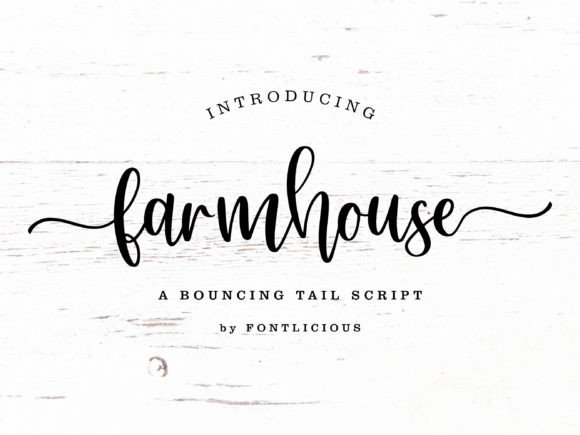
Farmhouse
์˜ฌ๋ฐ”๋ฅธ ๋””์ž์ธ ์š”์†Œ๋ฅผ ์ฐพ๋Š” ๊ฒƒ์€ ์–ด๋ ค์šธ ์ˆ˜ ์žˆ์ง€๋งŒ Farmhouse๋Š” ์ž‘์—…์„ ์ฆ‰์‹œ ํ–ฅ์ƒ์‹œํ‚ค๋Š” ๋›ฐ์–ด๋‚œ ์ปฌ๋ ‰์…˜์„ ์ œ๊ณตํ•ฉ๋‹ˆ๋‹ค.
์ •๋ฐ€ํ•˜๊ฒŒ ์ œ์ž‘๋œ Farmhouse๋Š” ๊น”๋”ํ•œ ๋ฒกํ„ฐ, ๋ถ€๋“œ๋Ÿฌ์šด ํƒ€์ดํฌ๊ทธ๋ž˜ํ”ผ ๋ฐ ์•ˆ์‹ฌํ•  ์ˆ˜ ์žˆ๋Š” ์ƒ์—…์šฉ ๋ผ์ด์„ ์Šค๋ฅผ ์ œ๊ณตํ•ฉ๋‹ˆ๋‹ค.
POD(์ฃผ๋ฌธํ˜• ์ธ์‡„) ์ œํ’ˆ, ๊ฒฐํ˜ผ์‹ ์ดˆ๋Œ€์žฅ ๋˜๋Š” ์†Œ์…œ ๋ฏธ๋””์–ด ๊ทธ๋ž˜ํ”ฝ์„ ๋งŒ๋“ค ๋•Œ Farmhouse๋Š” ์ด์ƒ์ ์ธ ์„ ํƒ์ž…๋‹ˆ๋‹ค.